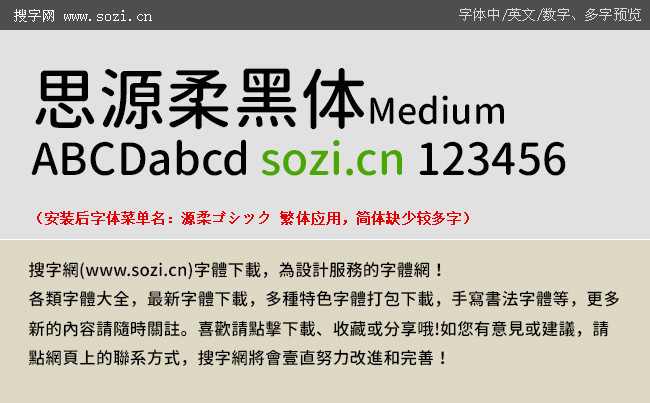
思源柔黑Medium
搜字網(wǎng)給大家提供一款思源柔黑Medium中文字體下載,思源柔黑體由思源黑體改造而來(lái),由日本作者自家製フォント工房制作,所以部分簡(jiǎn)體中文可能會(huì)不顯示,字柔黑承襲了「思源黑體」原有的優(yōu)雅,在文字邊角以圓邊進(jìn)行處理,相比原來(lái)思源黑體更加柔和,似黑似圓,介于二者之間。適用于大標(biāo)題、包裝設(shè)計(jì)、海報(bào)設(shè)計(jì)等應(yīng)用。